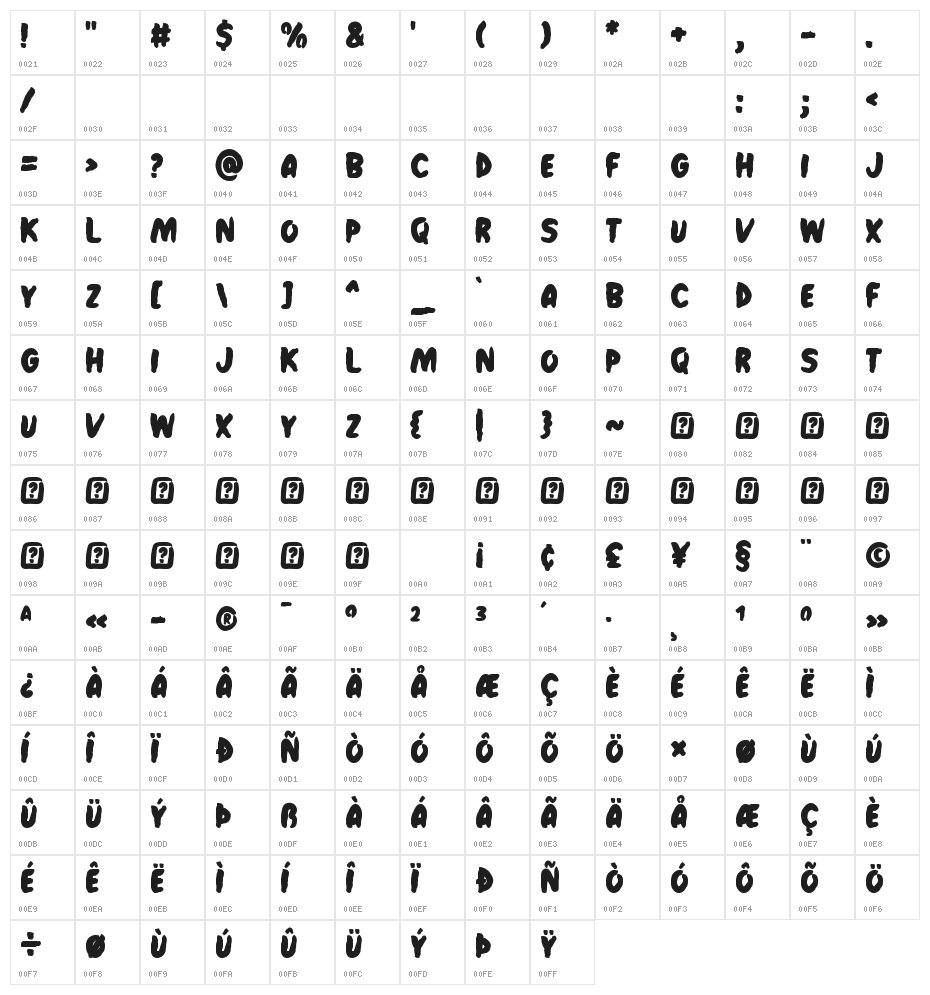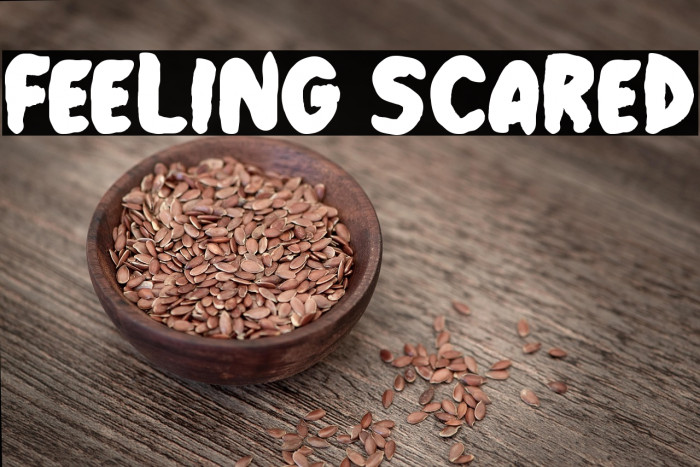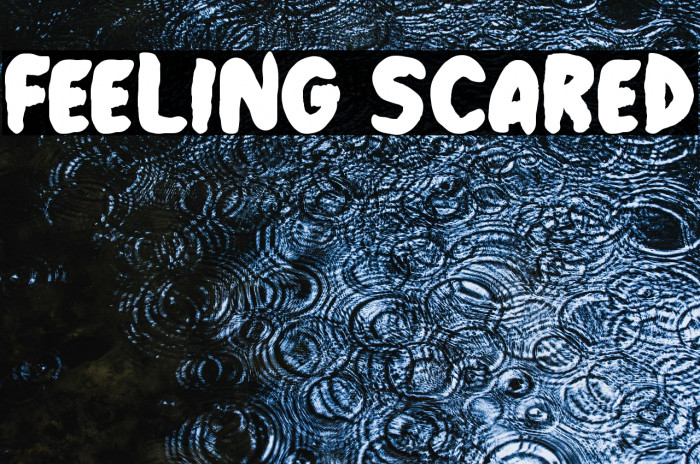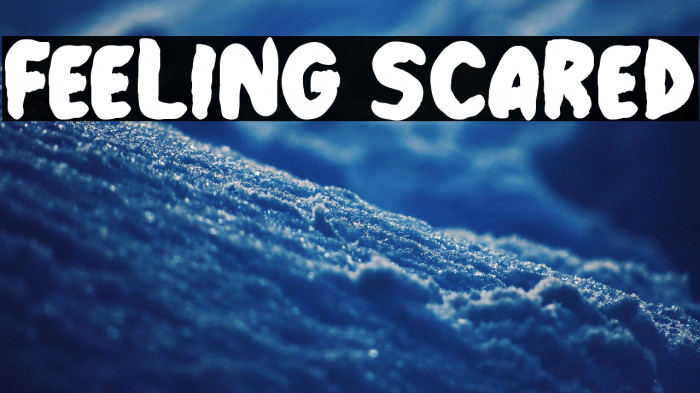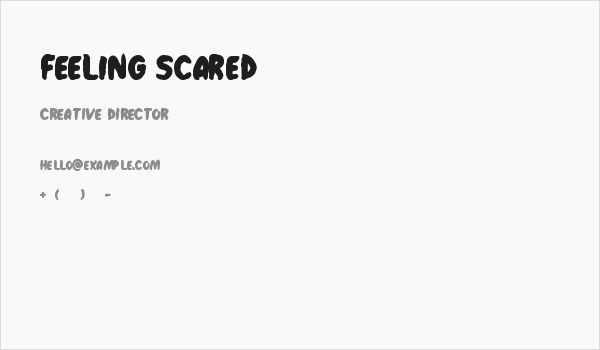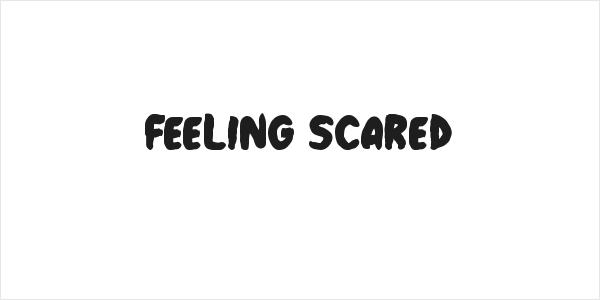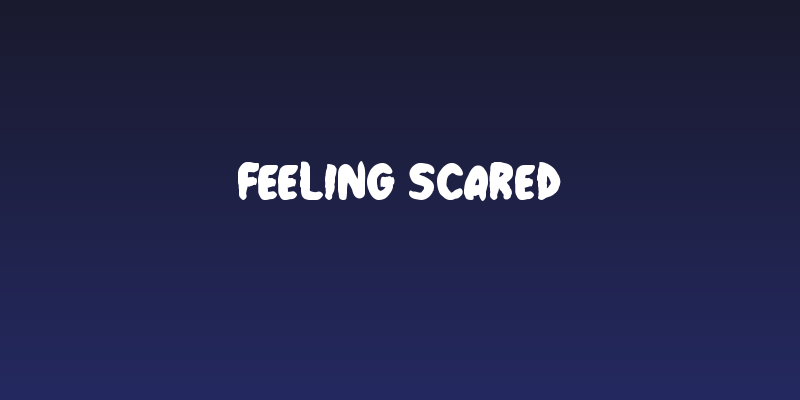
Feeling Scared Font
| Gesamtstil | Playful, Creative |
| Vorgeschlagene Projekte | Ideal for children's book covers, playful branding, posters, and creative social media graphics. |